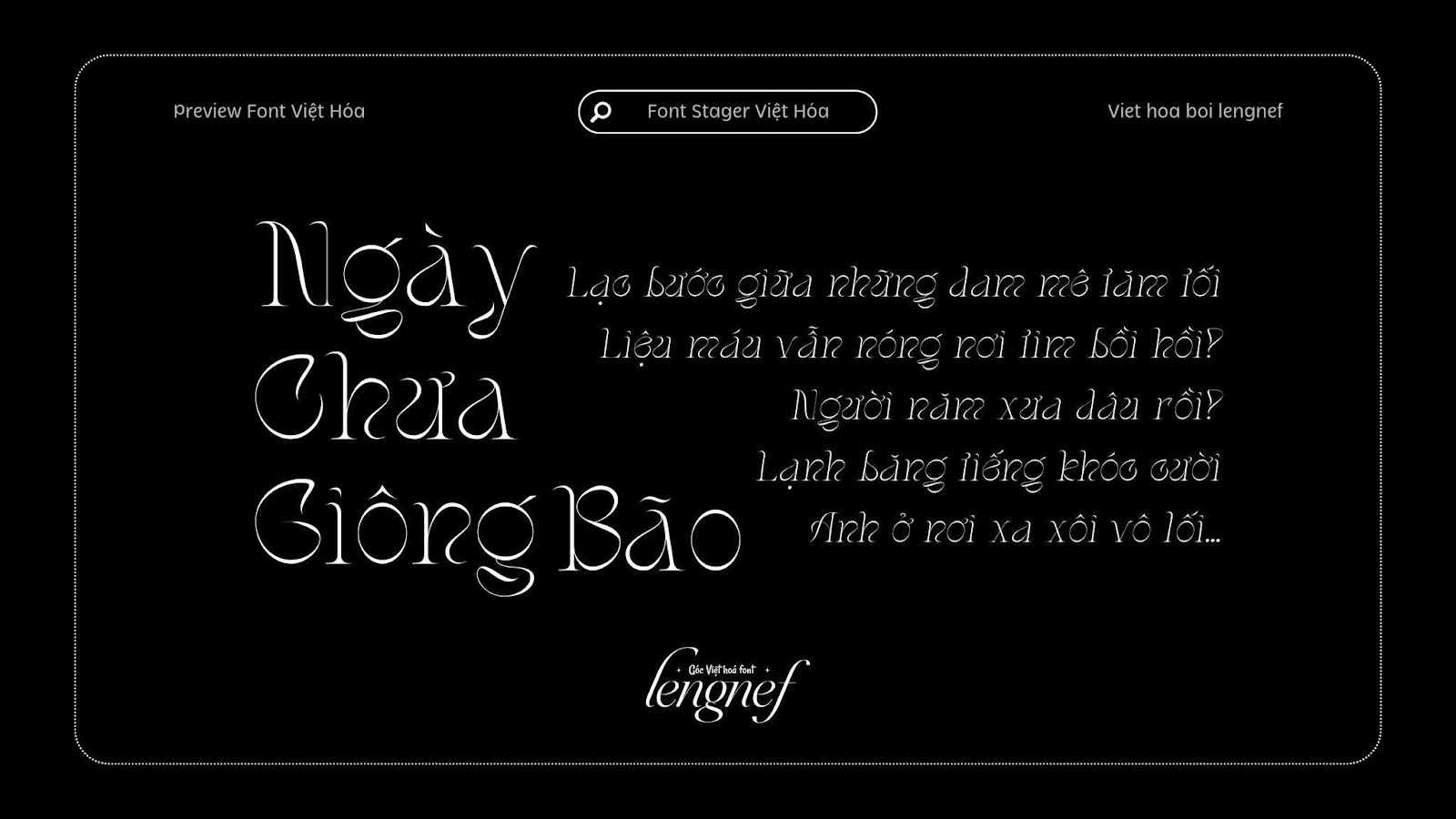
Share Font 09 || LF Stager
- Tác giả: Dharmas Studio
- Việt hóa: lengnef
Stager – Một phông chữ serif thanh lịch với nét nghệ thuật, độc đáo và sang trọng, đưa chúng ta trở về thời kỳ hoài cổ. Cấu trúc chữ mảnh mai kết hợp với các ký tự thay thế độc đáo và các đường nối đẹp mắt, giúp mọi dự án trở nên sang trọng, tối giản, độc đáo, nghệ thuật, mang hơi hướng art decor.
Stager có cả phiên bản chữ nghiêng (Italic) hoàn toàn phù hợp để tạo ra các thiết kế trang nhã, đơn giản, mang hơi hướng retro như thiết kế thương hiệu, áp phích, sách, thời trang, thiết kế mạng xã hội, logo, v.v…